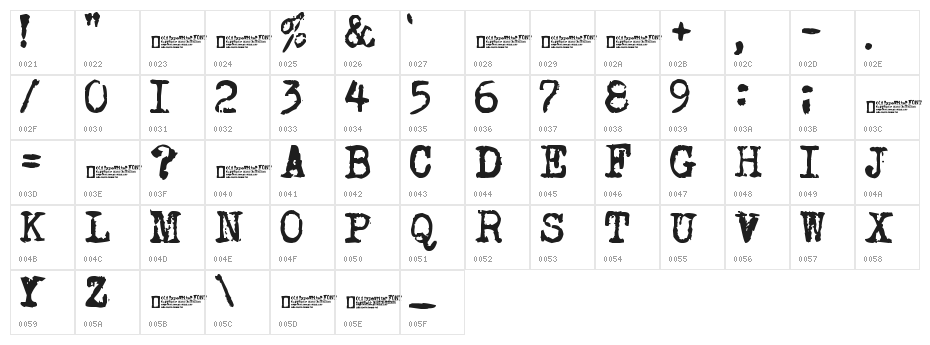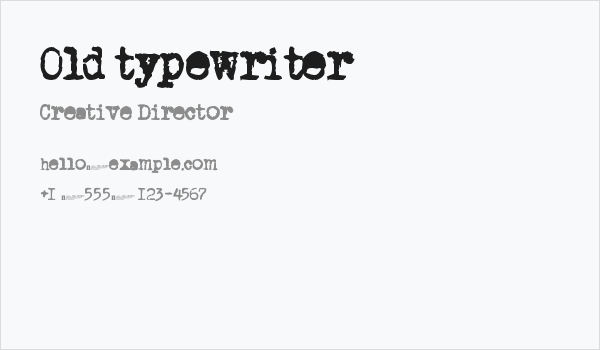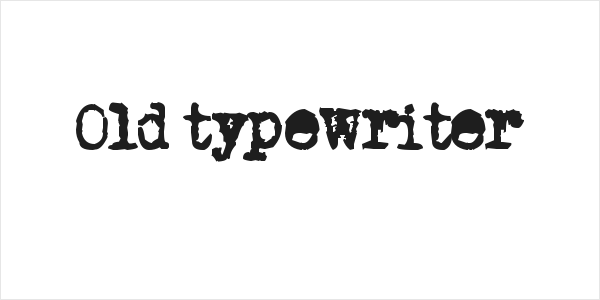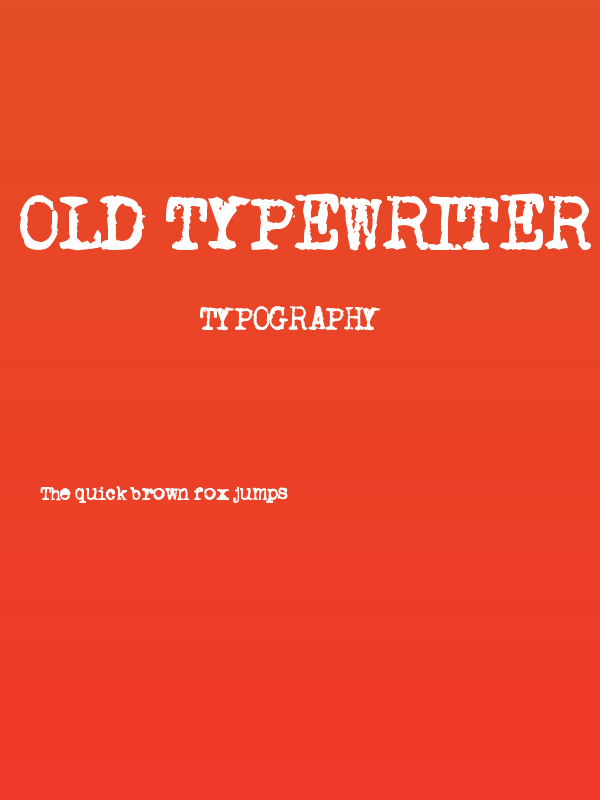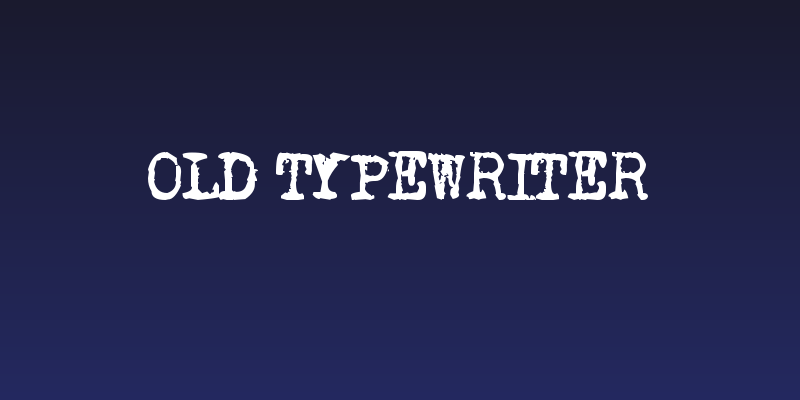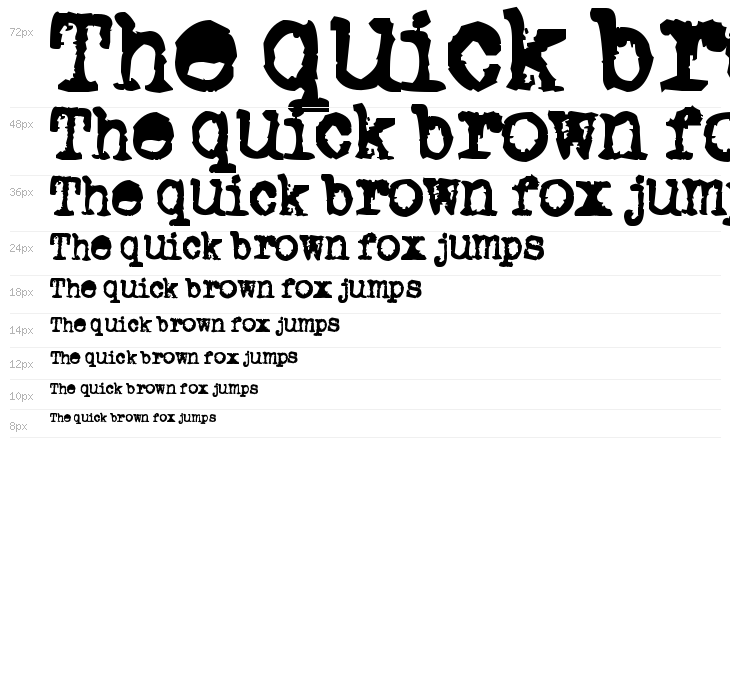
Old typewriter Font
| Gesamtstil | Vintage |
| Vorgeschlagene Projekte | Ideal for retro-themed designs, vintage posters, book covers, and creative projects that require a nostalgic or aged look. |